書籍『文字とタイポグラフィの地平』に秀英体が掲載されました
2015年11月5日に発売の「アイデア・ドキュメント 文字とタイポグラフィの地平」に秀英体の記事が掲載されました。
デザイン環境がDTPへと移行した90年代半ば以降、国内外でタイポグラフィへの関心が高まったことを受け、デザイン誌「アイデア」でもさまざまな事例や研究が紹介されてきました。
本書はその中から記事約30本を再録したものです。古今東西のタイポグラフィについての考察、和文書体や日本語タイポグラフィの歴史研究やレポート、タイポグラフィについてのブックガイドなどを中心に収録されています。
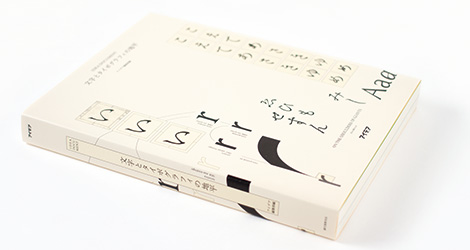
記事30本、432ページの厚み!
表紙左上には秀英明朝の「い」の変遷がレイアウトされています。一番上は活字の原図(昭和42年)、次に昭和後期にデジタル化されたもの、下が現在の「平成の大改刻」でリニューアルした秀英明朝です。
また、本書のタイトル、目次や奥付などには秀英明朝が使用されています。
秀英体の記事は、「秀英体──平成の大改刻」と題して、リニューアルプロジェクト「平成の大改刻」の開発者の談話や書体見本、秀英体の100年の歴史をご紹介する年表など、16ページにおよぶ充実の内容です。(2011年2月10日発売の「アイデア No.345」からの再録です。)